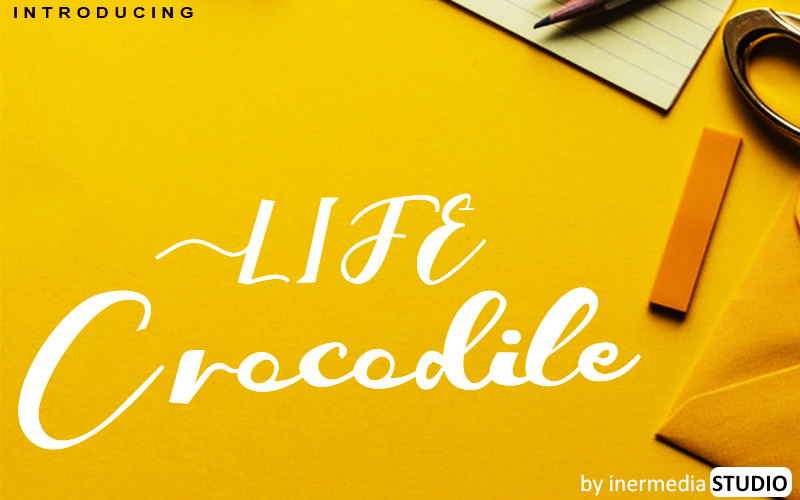
Crocodile Font – Fonte Grátis
Crocodile Font
A Crocodile Font é uma fonte criada com um toque elegante para quem gosta de adicionar personalidade às suas criações digitais. Esta fonte especializada na arte manual tem a capacidade única de transformar qualquer projeto DIY em algo único e impressionante. Ideal para aqueles que desejam dar vida aos seus projetos casuais, este belo e singular handwritten font é uma escolha perfeita para quem busca fazer algo realmente especial com suas criações. Seja um adesivo personalizado, uma t-shirt única ou até mesmo uma estampagem de móveis, a Crocodile Font pode transformar seu trabalho em algo realmente memorável. Experimente e descubra como esta fonte pode dar vida à sua criatividade.